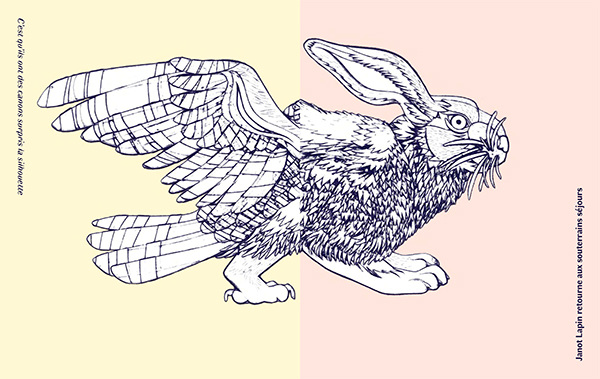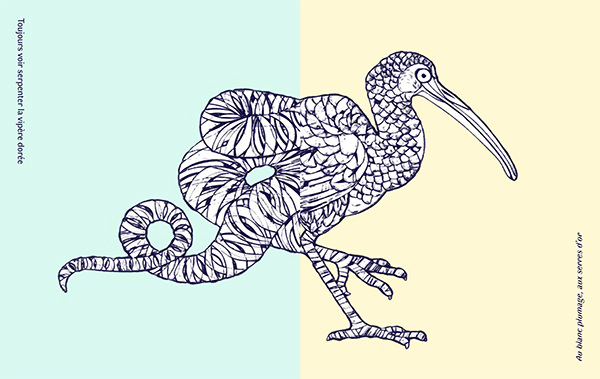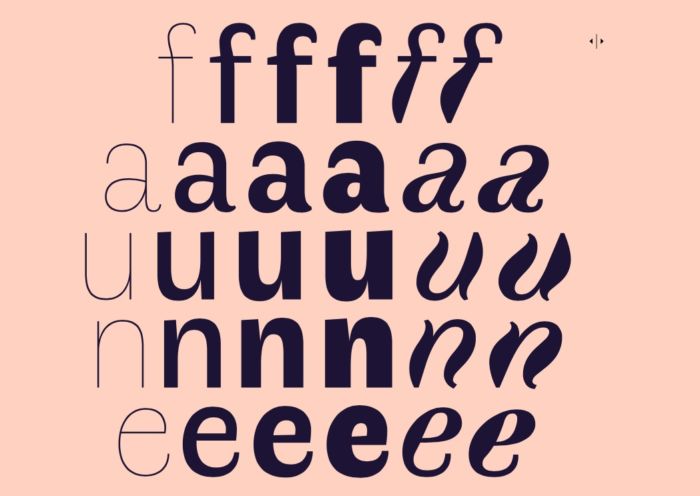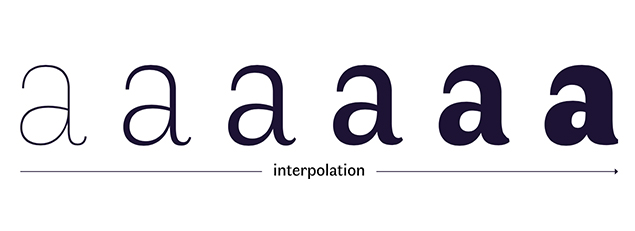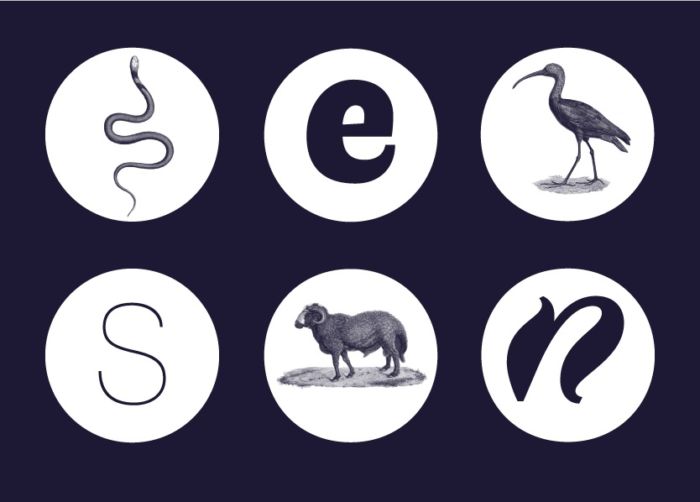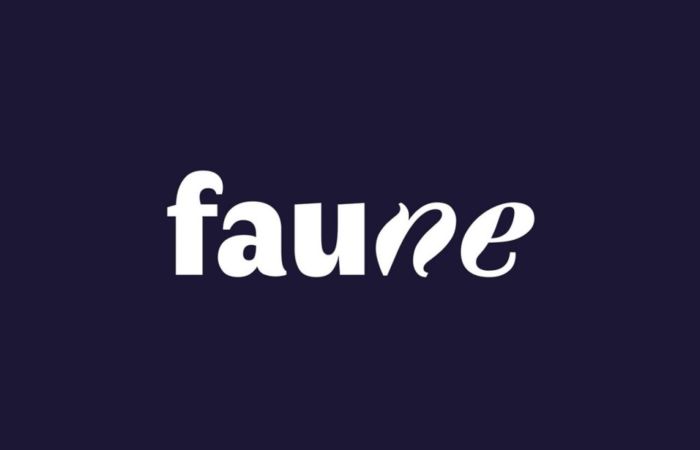
Faune, una tipografía gratuita inspirada en el reino animal
tipografía gratuita inspirada en el reino animal
Comencemos el día compartiendo un recurso de lo más interesante para los diseñadores amantes de los animales; se trata de la obra de Alice Savoie, una tipógrafa que gano el concurso del Centro Nacional de Artes plásticas francés.
Faune es una fuente gratuita que podrás descargar en este enlace; que esta inspirada en el reino animal y más congruentemente en las obras “Historia natural de Buffon (1749-1788)” y “Descripción de Egipto (1809-1830)”; dos obras de carácter científico que contienen información sobre diferentes especies animales.
“A partir de tres clases de animales vertebrados: reptiles, mamíferos y pájaros, se imaginó tres caracteres tipográficos, creando las bases de una familia heteróclita” señala AliceSavoie
Tipografía gratuita inspirada en el reino animal
Lo anterior quiere decir que si bien cada letra no esta inspirada en animales distintos; las conformación de letras negrita, itálica y la clásica están inspiradas en diferentes especies; como se muestra en el gráfico anterior.